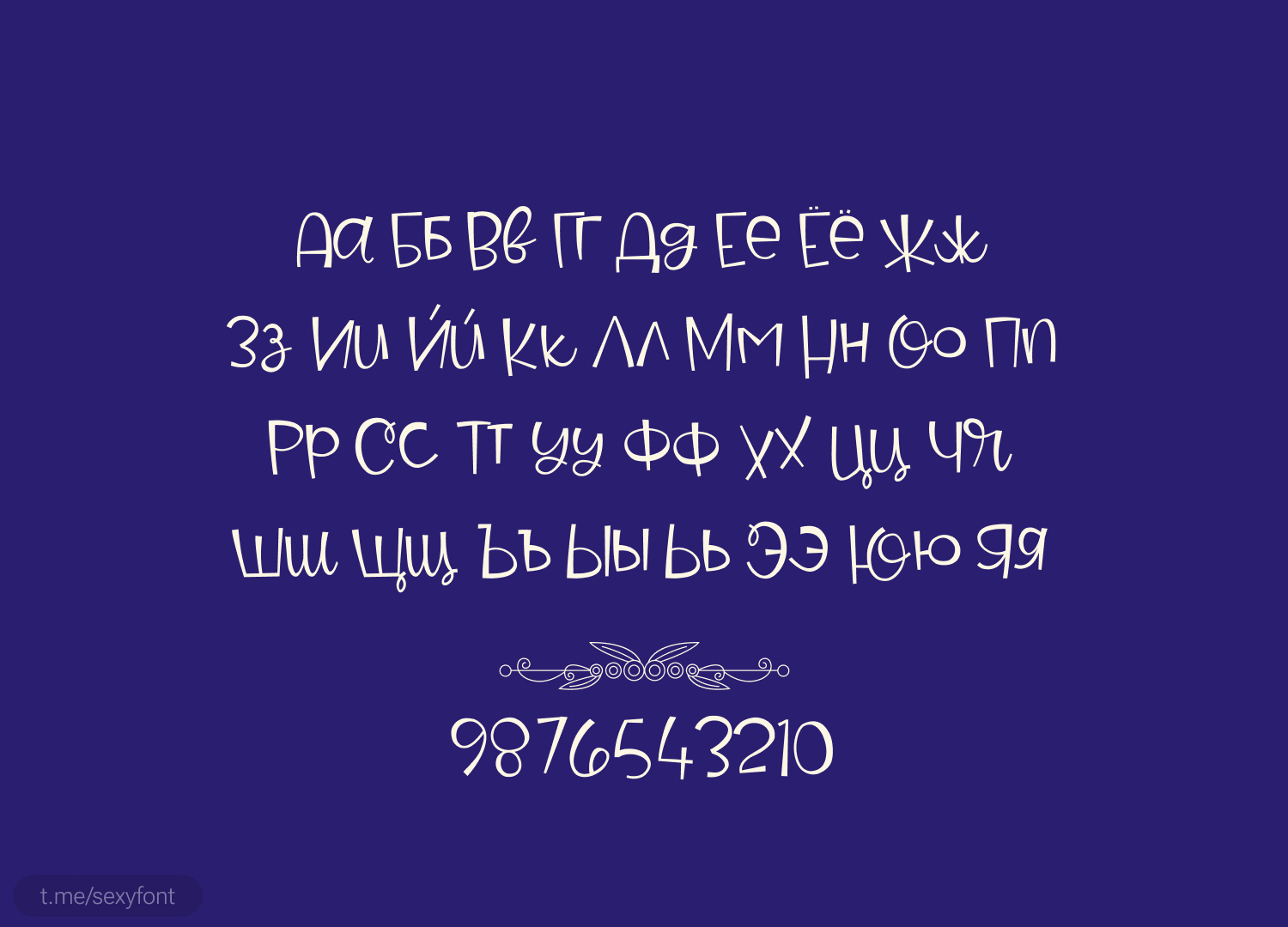
Шрифт birdy
Шрифт birdy. Красивый декоративный шрифт для заголовков. Нравится, как отличаются строчные и прописные буквы) Из можно легко чередовать в каждом слове.